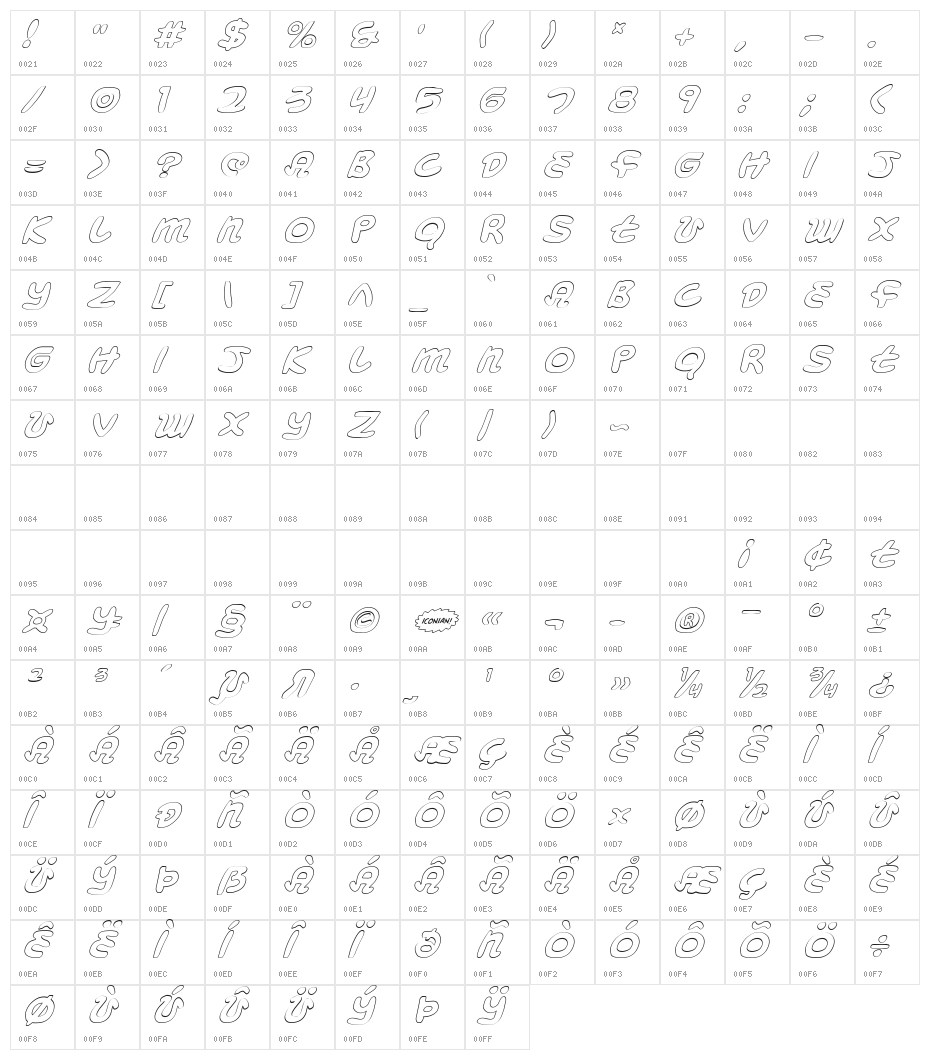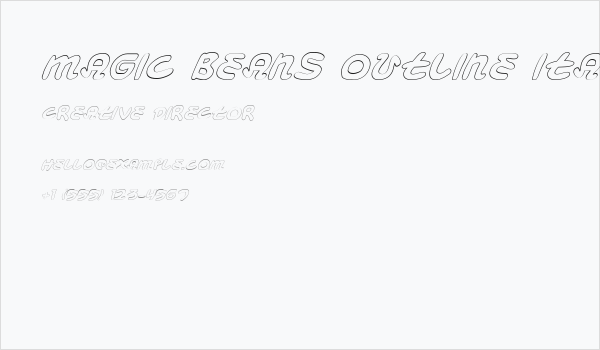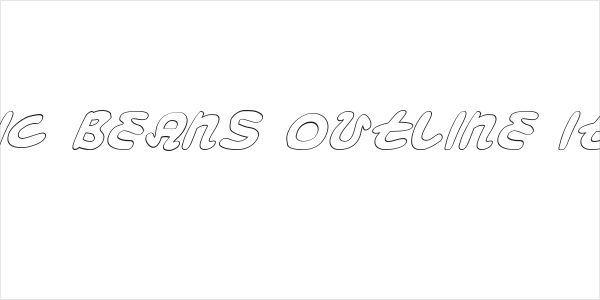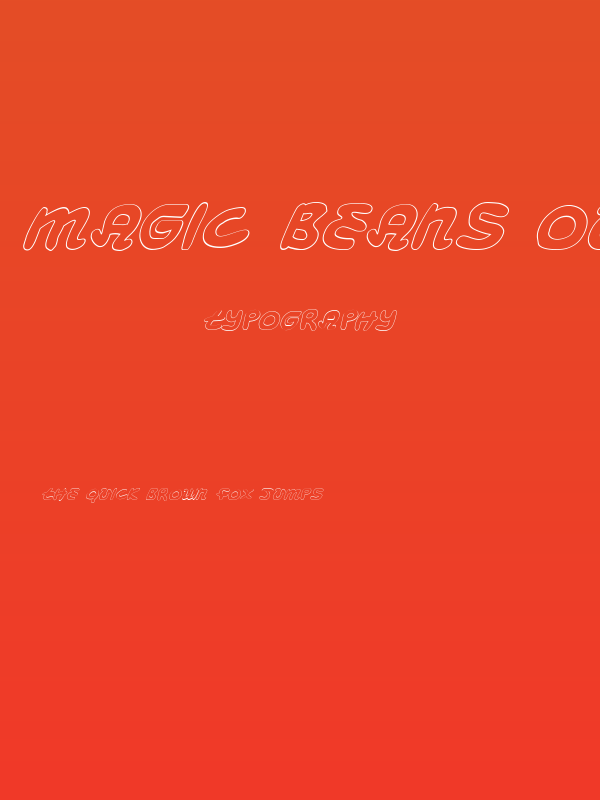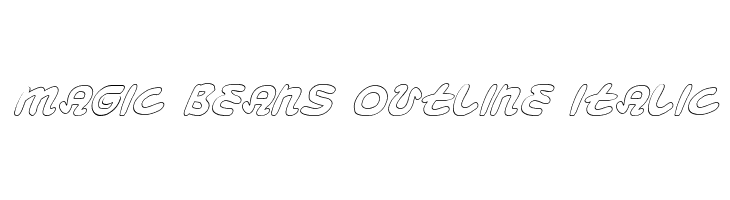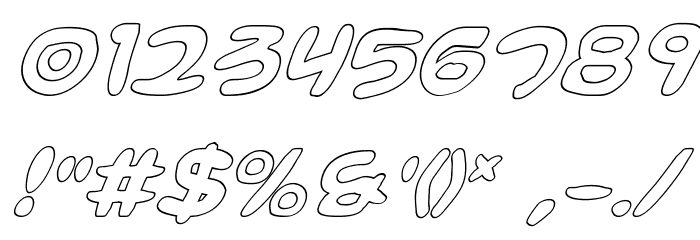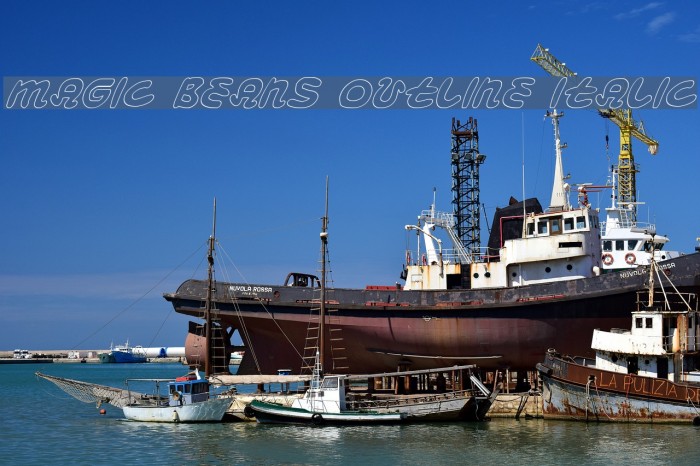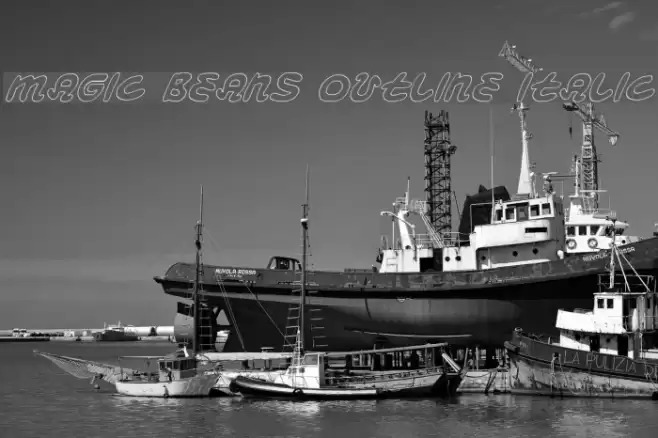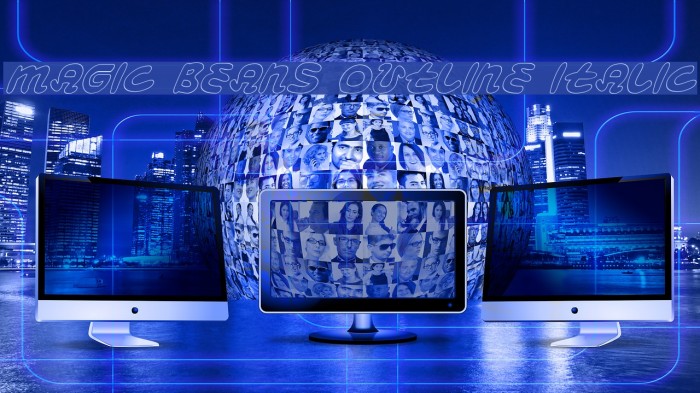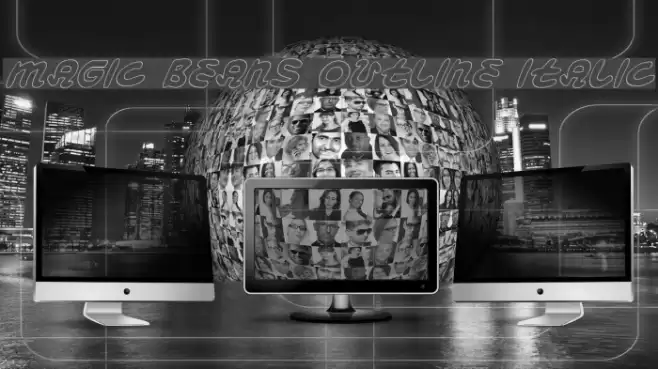
Magic Beans Outline Italic Font
| Style général | Playful |
| Cas d'utilisation | Headlines, Logos, Creative projects |
| Projets proposés | Ideal for children's books, playful branding, greeting cards, and creative posters. |